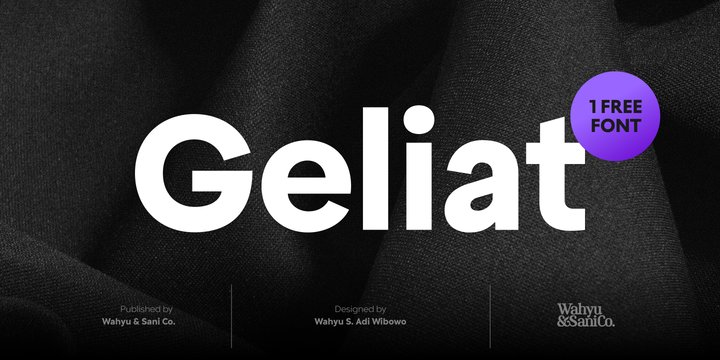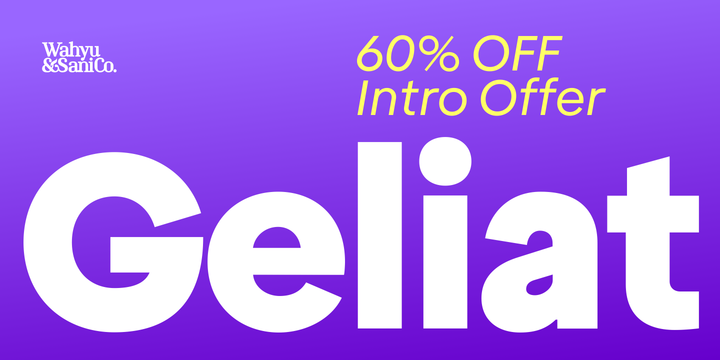
Гелиат был бы младшим братом Крео, сохранив форму буквы и пропорции, но имея более геометричный вид. Это семейство шрифтов поставляется в двух версиях, которые имеют несколько различных глифов по умолчанию. Семейство Geliat имеет похожую форму букв с крео, в то время как версия Alt имеет общую геометрическую форму букв.
Курсивные стили Geliat были разработаны полуроталическим методом. Круглая часть имеет угол 5 градусов, а вертикальные штрихи сделаны в 10 градусов. В результате стили выглядят более круглыми, чем большинство геометрических шрифтов с одинаковым углом наклона в 10 градусов.
Каждая версия Geliat имеет 2 переменных шрифта
, а также 10 различных предопределённых весов от тонкого до тяжёлого с соответствующим курсивом. Каждый член семейства Geliat также оснащен полезными функциями OpenType, такими как Ordinals, Superscripts, Scientific Inferiors, Stylistic Sets, Tabular Lining, Standard Ligatures, Fraction, Numerators & Denominators. Каждый шрифт имеет 500+ глифов, которые охватывают Западную и Восточную Европу, а также другие языки, основанные на латинице.
Geliat подойдет для многих творческих проектов, от логотипов, плакатов, презентаций, заголовков, надписей, брендинга, цитат, заголовков, журналов, заголовков, веб-баннеров, мобильных приложений, художественных цитат, рекламы, дизайна упаковки, заголовков книг и многого другого! Небо - это предел!